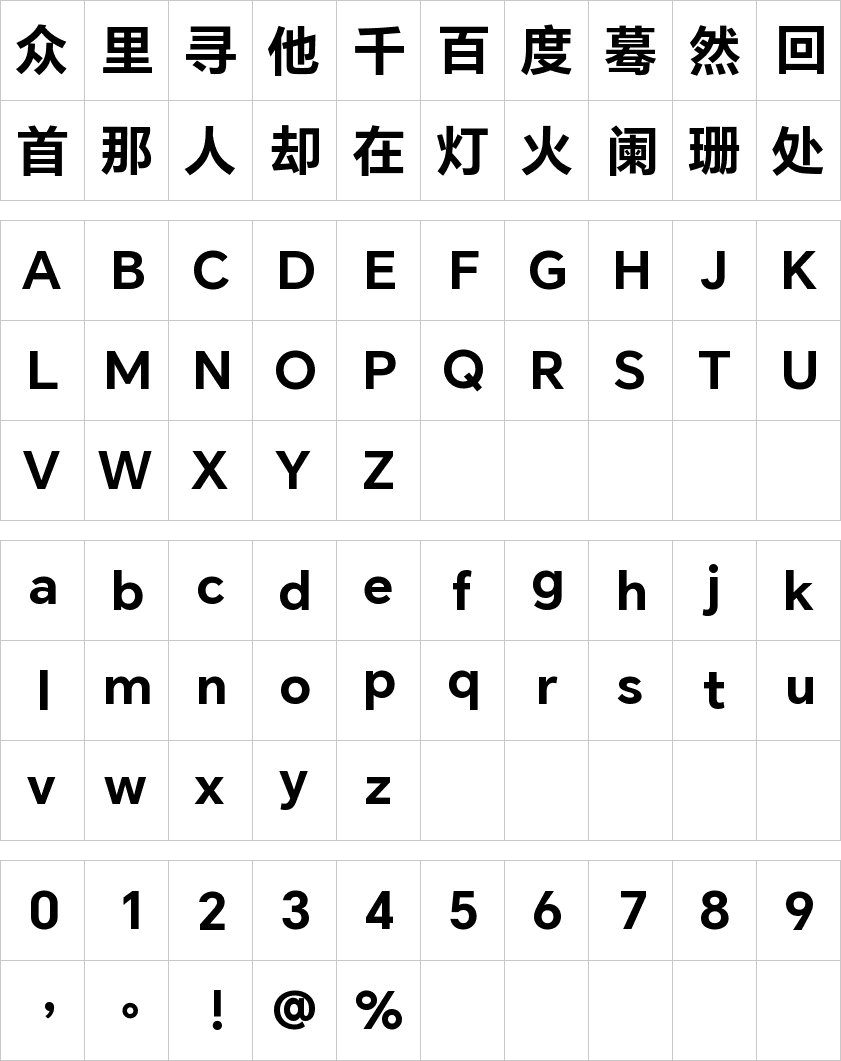
荣耀字体:HONOR Sans
在荣耀 MagicOS 7.0 发布会上,荣耀还带来了全新的荣耀字体(HONOR Sans) 字体,号称是业界首款支持字重和中宫双重无极可变的字体,将荣耀字体与 UI 融合,通过间距优化,让排版更整齐,层次更清晰。
HONOR Sans以黑体为基础,为创作者带来了一种新的黑体选择,在海报、视频字幕、说明文字等方面都能充分起到作用。